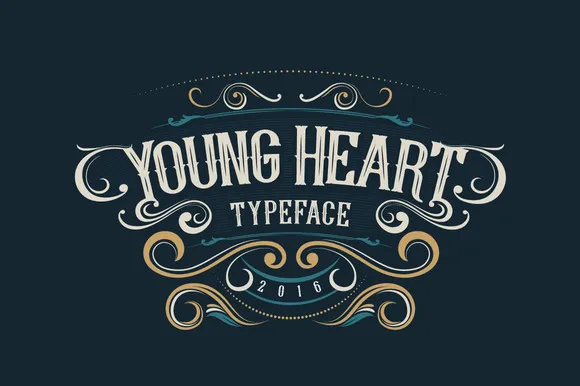
Young Heart Font – Fonte Grátis
Young Heart Font
A fonte ‘Young Heart’ é uma escolha perfeita para aqueles que buscam uma fonte decorativa com personalidade. Desenvolvida pelo designer Hamilton, esta fonte é ideia para designers gráficos e aspirantes a designers, oferecendo um toque encantador que torna qualquer projeto único e vibrante. Este font tem sido projetado não apenas para uso pessoal, mas também para aplicações comerciais. Acredita-se que cada detalhe foi cuidadosamente pensado para garantir uma experiência de escrita fluida e leitura fácil, o que a torna perfeita para aplicativos como banners de marketing, logotipos, cartazes e até mesmo materiais de publicidade. Com um design delicado, essa font traz à tona elementos joviais e animados, dando ao seu projeto uma aparência que emociona e captura o coração do consumidor. Não apenas uma ferramenta útil para os designers, mas também uma peça essencial para qualquer designer gráfico buscando criar algo especial e único. Se você aprecia este produto, é sempre incentivado a dar um pequeno valor de volta ao designador Hamilton. Sua ajuda não só fortalece o trabalho dele, como também pode beneficiar futuras criações e recursos gráficos disponíveis para o público.